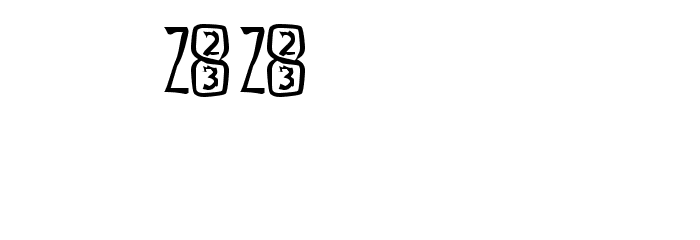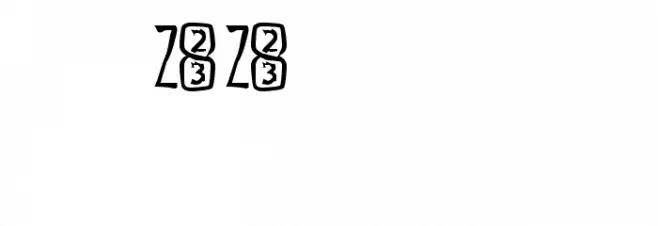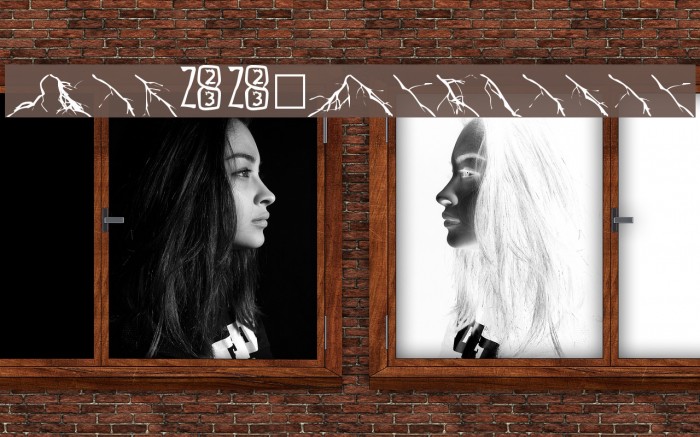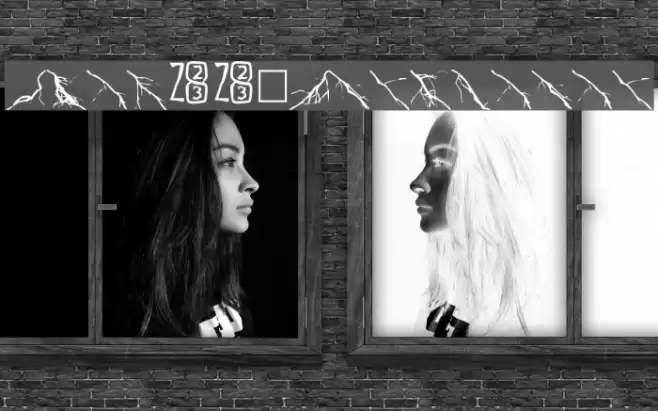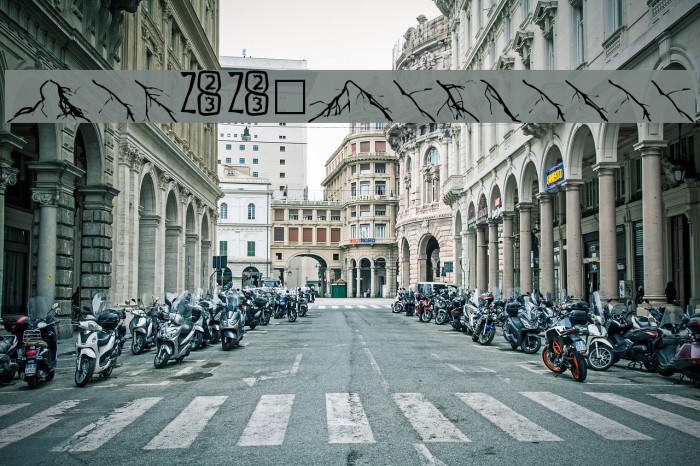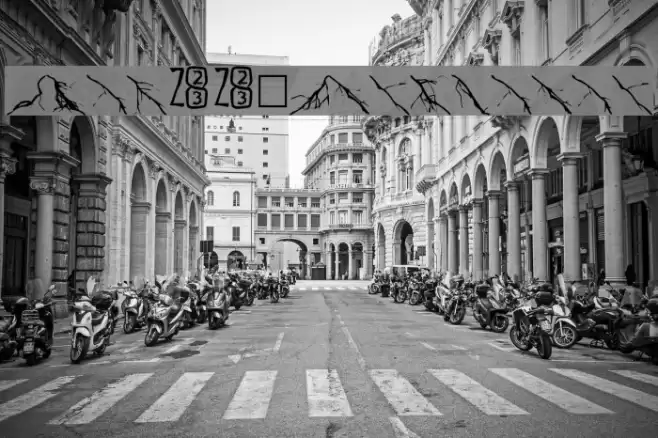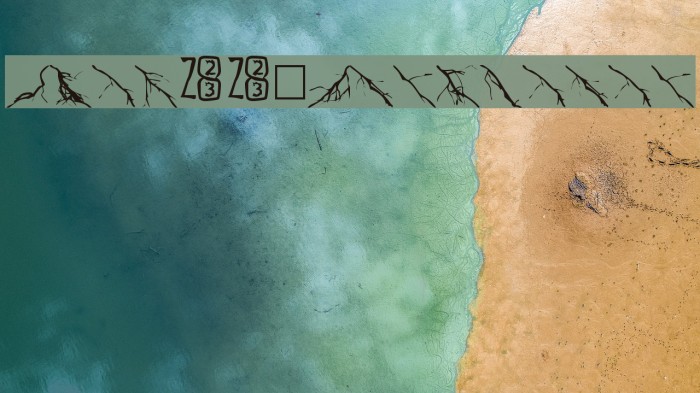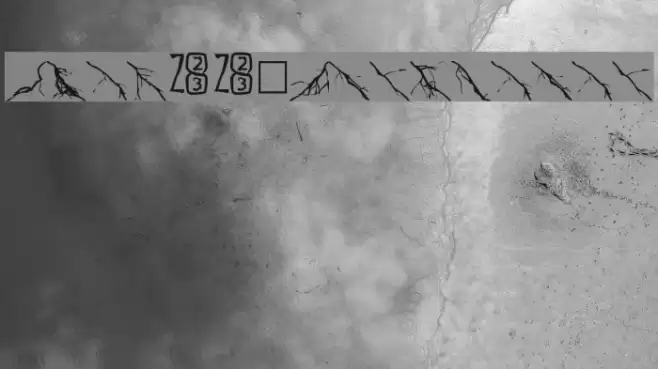
Zone23_Lightning Font
| Proyectos propuestos | Ideal for projects that require a bold and energetic aesthetic, such as event posters, album covers, or branding for extreme sports. |